Top 15 font chữ cho giao diện app, dashboard và landing page tiếng Việt
Gợi ý 15 font TH Việt hóa phù hợp cho giao diện app, dashboard, landing page và website tiếng Việt: dễ đọc, hiện đại và dùng tốt cho UI.
Font cho giao diện app, dashboard và landing page không giống font làm poster. Với UI, chữ phải đọc nhanh, rõ dấu tiếng Việt, giữ được độ ổn định ở kích thước nhỏ và không làm người dùng mỏi mắt khi nhìn lâu. Một font đẹp nhưng quá trang trí có thể rất hợp với key visual, nhưng khi đưa vào bảng số liệu, form đăng nhập, menu sidebar hoặc mô tả tính năng thì lại làm trải nghiệm kém đi.
Khi thiết kế giao diện tiếng Việt, dấu chữ là vấn đề cần kiểm tra sớm. Các cụm như "quản lý đơn hàng", "bảng điều khiển", "cập nhật tài khoản", "thanh toán thành công" hoặc "đăng ký dùng thử" có nhiều dấu ở phía trên và phía dưới. Nếu font không Việt hóa tốt, UI sẽ nhanh lộ lỗi: dấu lệch, dòng bị chật, chữ vỡ nhịp hoặc khoảng cách nhìn không đều.
Bài viết này gợi ý 15 font TH Việt hóa phù hợp cho app, dashboard, landing page, website tiếng Việt và các sản phẩm số cần cảm giác hiện đại, rõ ràng.
Tiêu chí chọn font UI tiếng Việt
Dễ đọc ở kích thước nhỏ
Trong dashboard, nhiều chữ chỉ hiển thị ở cỡ 12-16px: nhãn biểu đồ, menu, trạng thái đơn hàng, nút lọc, mô tả trường nhập liệu. Vì vậy, font UI nên có cấu trúc chữ rõ, khoảng cách không quá chật và dấu tiếng Việt không bị dính vào thân chữ.
Có nhiều sắc độ hoặc dễ tạo phân cấp
Một giao diện tốt cần nhiều cấp chữ: heading, subheading, body, caption, label, button, số liệu và cảnh báo. Nếu font có nhiều weight như regular, medium, bold hoặc black, designer sẽ dễ tạo hệ thống typographic nhất quán hơn.
Phù hợp với tính cách sản phẩm
App tài chính cần cảm giác tin cậy. Dashboard SaaS cần hiện đại và gọn. Landing page mỹ phẩm cần mềm hơn. Website giáo dục cần thân thiện. Vì vậy, không có một font dùng tốt cho mọi trường hợp. Hãy chọn font theo ngành, sau đó kiểm tra lại khả năng đọc ở giao diện thật.
Top 15 font TH cho app, dashboard và landing page
1. TH Legacy Sans - font sans-serif hiện đại cho UI nhiều thông tin
TH Legacy Sans là lựa chọn an toàn cho giao diện cần nhiều chữ: dashboard, app quản lý, trang cài đặt tài khoản, form đăng ký, trang pricing hoặc landing page B2B. Font có tinh thần hiện đại, gọn và không quá trang trí nên giúp nội dung giữ được sự rõ ràng.
Bạn có thể dùng TH Legacy Sans cho body text, menu, label, button và cả heading phụ. Với landing page, font này hợp với bố cục sạch, nhiều khoảng trắng, bảng tính năng và CTA rõ ràng.
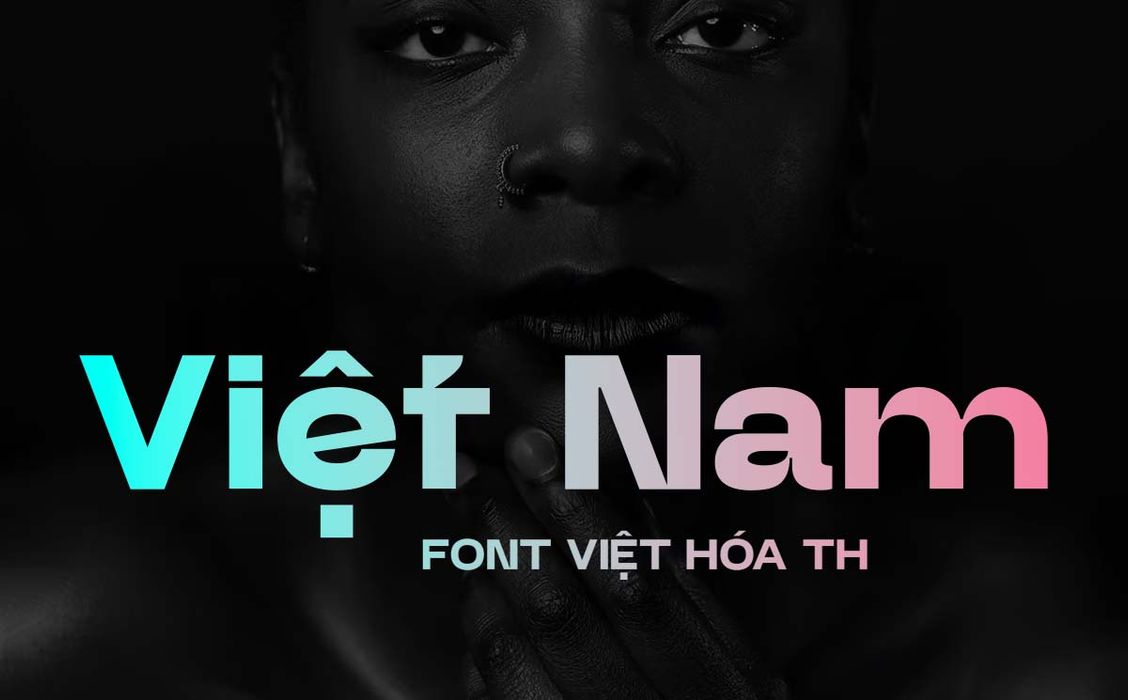
2. TH Guton - bộ font nhiều style cho dashboard và tài liệu sản phẩm
TH Guton phù hợp với các giao diện cần phân cấp rõ vì có nhiều style từ regular đến black. Đây là kiểu font đáng dùng cho dashboard, trang quản trị, app học tập, slide sản phẩm, tài liệu onboarding hoặc landing page có nhiều block nội dung.
Điểm mạnh của TH Guton là dễ tạo nhịp chữ: regular cho nội dung, medium cho label, bold cho số liệu và black cho heading ngắn. Khi dùng cho dashboard, bạn nên giữ khoảng cách dòng thoáng để số liệu và tiếng Việt có dấu không bị bí.
3. TH Algance - font tối giản cho landing page hiện đại
TH Algance có tinh thần sans-serif tối giản, phù hợp với landing page SaaS, website startup, thương hiệu công nghệ, portfolio agency hoặc trang giới thiệu sản phẩm số. Font tạo cảm giác hiện đại mà không cần quá nhiều hiệu ứng.
Với landing page, TH Algance nên dùng cho headline, subheading, đoạn mô tả ngắn và CTA. Nếu dùng cho dashboard nhiều dữ liệu, hãy kiểm tra trước các bảng số liệu nhỏ để đảm bảo chữ không quá mảnh.
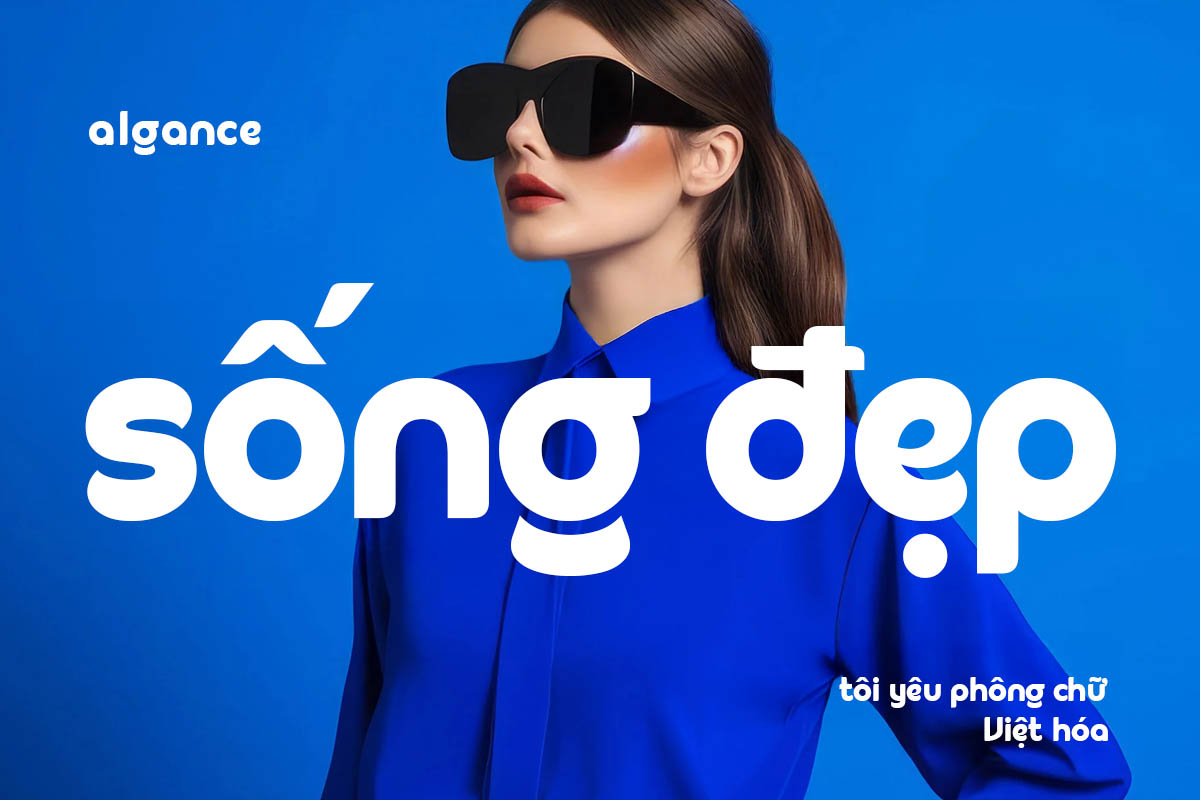
4. TH Giabe - sans-serif display cho hero và tiêu đề section
TH Giabe là font sans-serif display hiện đại, cá tính hơn các font UI trung tính. Font này hợp với hero landing page, banner trong app, tiêu đề section, cover sản phẩm, social post hoặc khu vực cần gây ấn tượng đầu tiên.
Không nên dùng TH Giabe cho toàn bộ body text nếu giao diện có nhiều chữ. Cách dùng tốt hơn là phối TH Giabe cho headline và dùng một font gọn hơn như TH Legacy Sans hoặc TH Guton cho nội dung phụ.
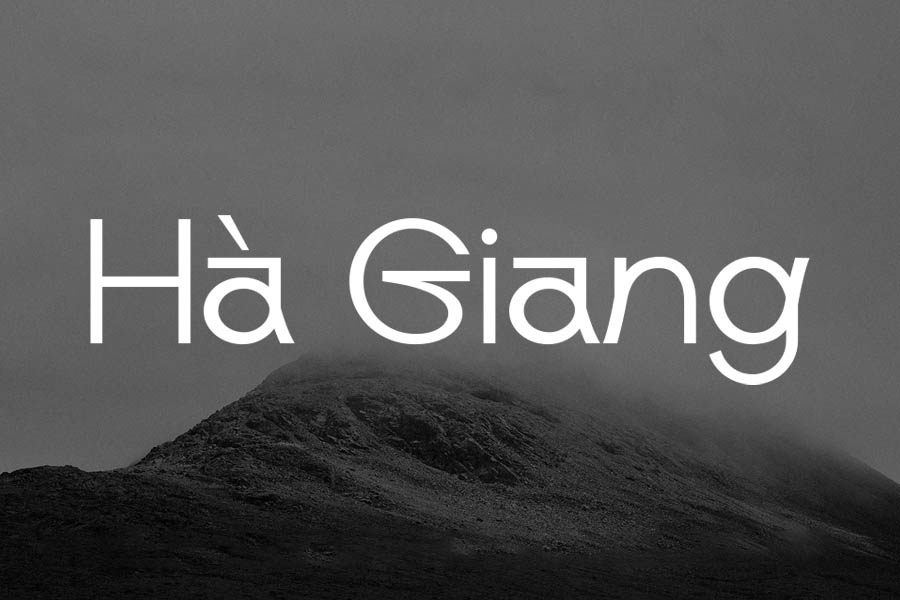
5. TH Grotley - luxury sans-serif cho landing page cao cấp
TH Grotley phù hợp với landing page sản phẩm cao cấp, app làm đẹp, dịch vụ tư vấn, khách sạn, clinic, spa hoặc thương hiệu cần cảm giác tinh tế nhưng vẫn hiện đại. Đây là font sans-serif có sắc thái luxury, dễ dùng hơn các font serif mảnh khi thiết kế giao diện.
Bạn có thể dùng TH Grotley cho heading, tên gói dịch vụ, số liệu nổi bật và CTA. Với đoạn mô tả dài, nên tăng line-height và giữ màu chữ đủ tương phản để giao diện không bị nhẹ quá.
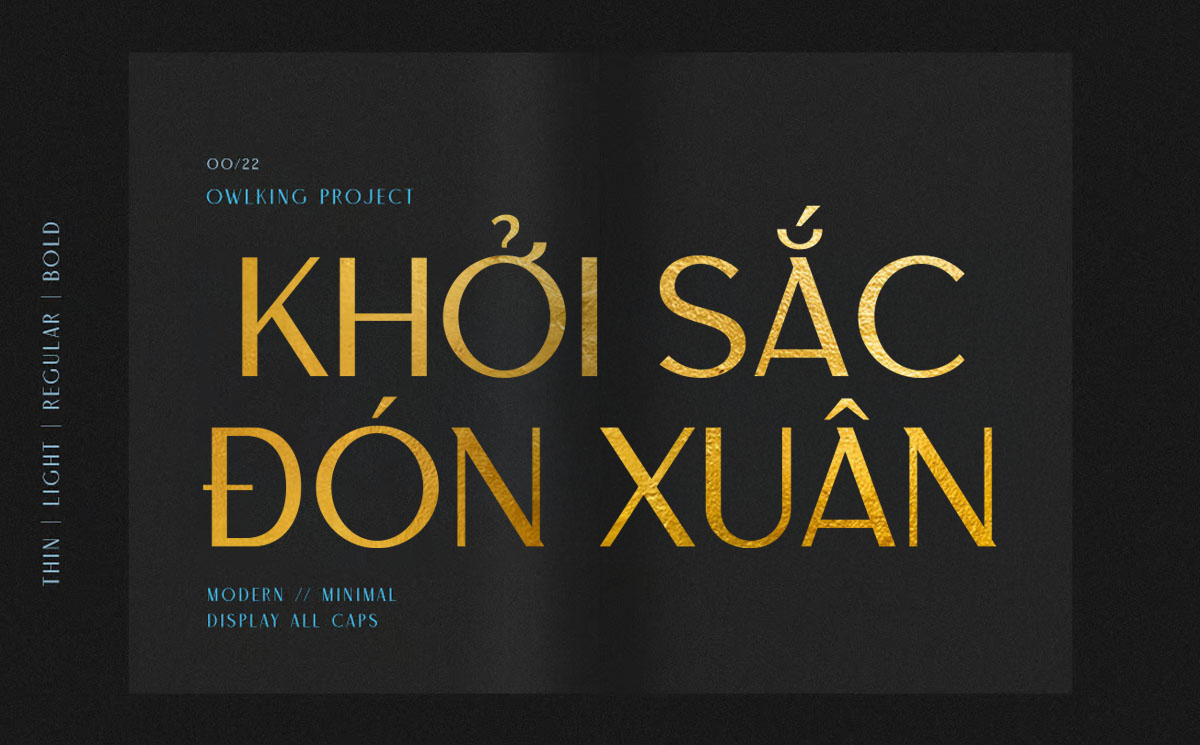
6. TH Selaris - font hiện đại cho app làm đẹp và landing page dịch vụ
TH Selaris hợp với các giao diện trong lĩnh vực làm đẹp, skincare, spa, clinic, tư vấn cá nhân hoặc dịch vụ lifestyle. Font tạo cảm giác hiện đại, mềm và có sự chăm chút, phù hợp với landing page cần độ tin cậy lẫn tính thẩm mỹ.
Khi dùng TH Selaris, hãy đặt font ở những khu vực cần cảm giác thương hiệu: headline, tên dịch vụ, card lợi ích, testimonial hoặc CTA. Với dashboard nội bộ nhiều bảng dữ liệu, nên phối thêm font phụ rõ hơn.
Xem mẫu và tải font TH Selaris Việt hóa.
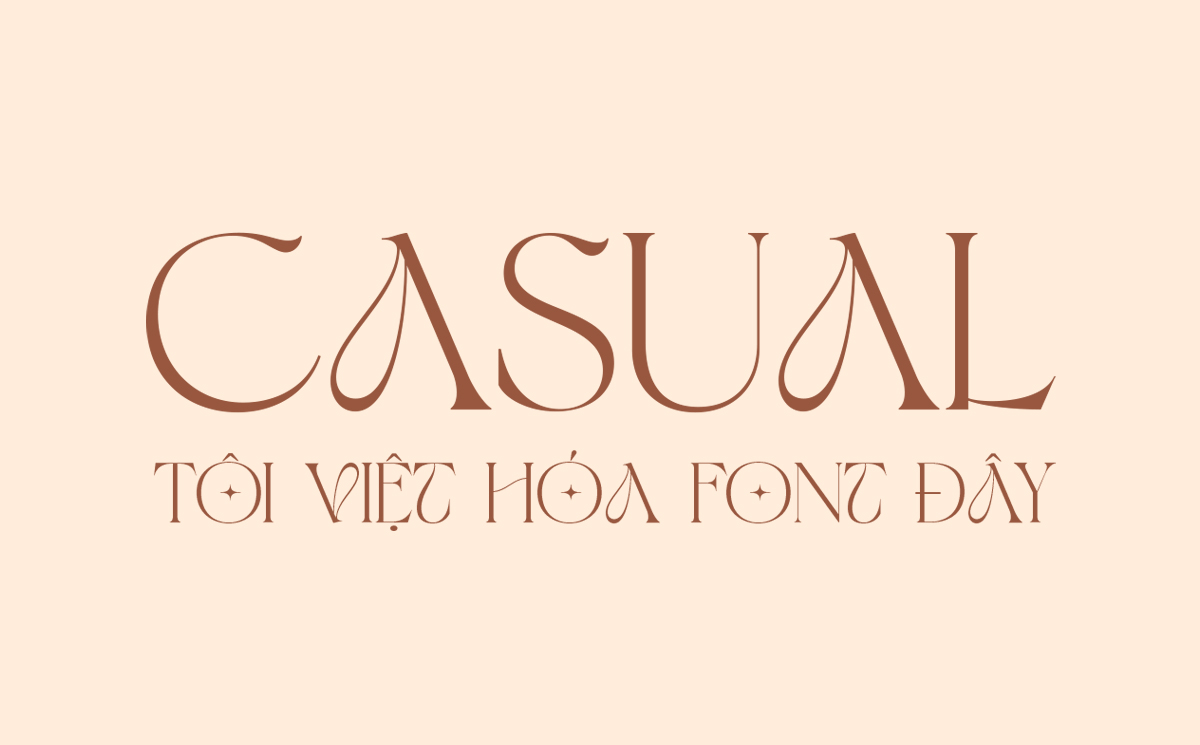
7. TH Milkalte - font hiện đại cho landing page cân sức, wellness và dịch vụ
TH Milkalte phù hợp với landing page wellness, fitness nhẹ, dịch vụ chăm sóc sức khỏe, app lifestyle hoặc trang giới thiệu sản phẩm có phong cách sạch và sang. Font có vẻ hiện đại, hợp với các layout nền sáng, ảnh sản phẩm và nhiều khoảng trắng.
Bạn nên dùng TH Milkalte cho tiêu đề, nhãn tính năng và các cụm chữ ngắn. Nếu landing page có nhiều đoạn mô tả dài, hãy kiểm tra độ đọc trên mobile vì người dùng thường đọc ở cỡ chữ nhỏ hơn desktop.
Xem mẫu và tải font TH Milkalte Việt hóa.
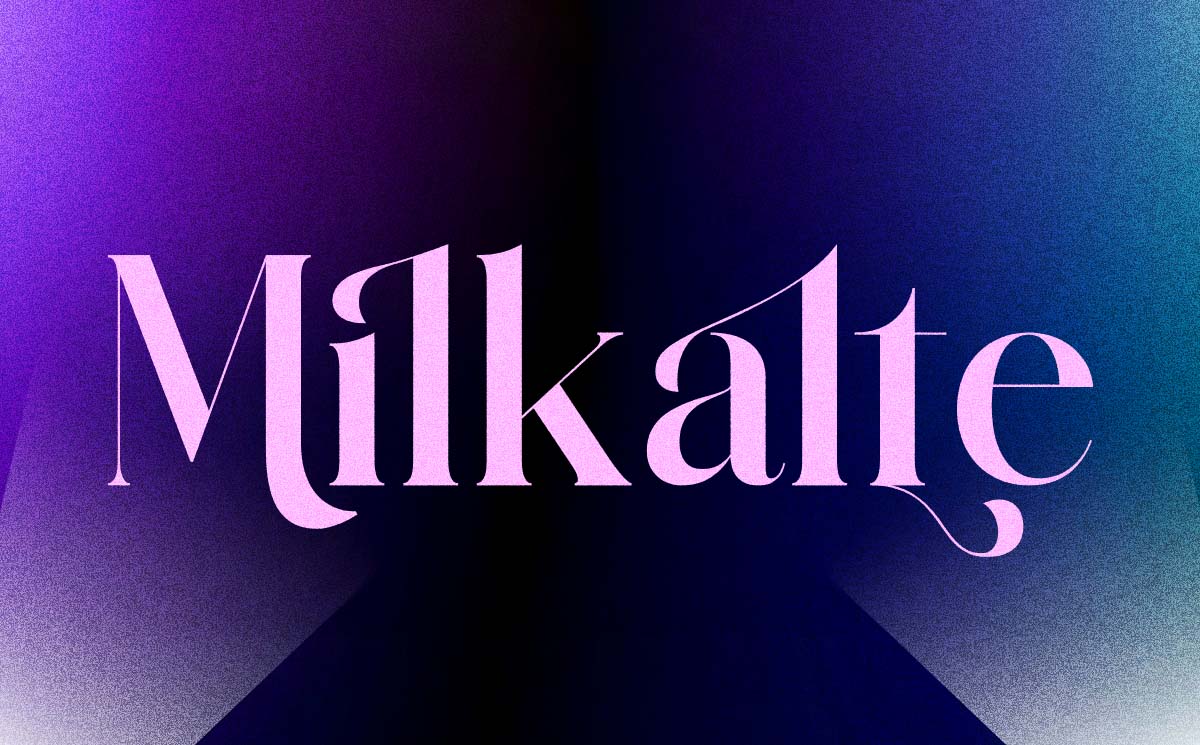
8. TH Mattire - font sang trọng cho website thương hiệu và trang giới thiệu
TH Mattire hợp với website thương hiệu, landing page dịch vụ cao cấp, trang giới thiệu agency, thời trang, mỹ phẩm hoặc các sản phẩm cần cảm giác tinh gọn. Font có chất hiện đại và sang, nhưng không quá kịch tính như font display poster.
Trong UI, TH Mattire nên dùng cho heading, số liệu nổi bật, tên gói dịch vụ hoặc section title. Với phần mô tả, bảng giá và form, hãy giữ chữ đủ lớn và khoảng dòng thoáng để tăng khả năng đọc.
Xem mẫu và tải font TH Mattire Việt hóa.
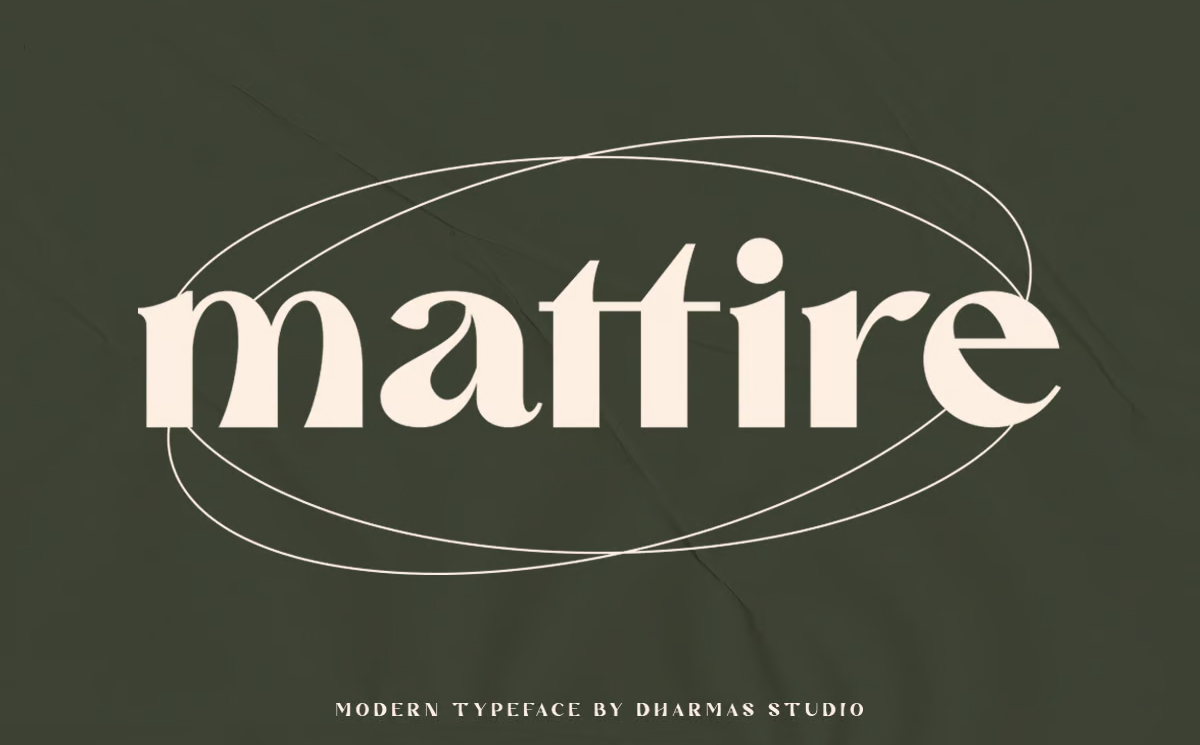
9. TH Bevas - font luxury hiện đại cho landing page sản phẩm
TH Bevas phù hợp với landing page mỹ phẩm, thời trang, phụ kiện, trang sức, khóa học premium hoặc dịch vụ tư vấn. Font có cảm giác luxury hiện đại, giúp phần hero và headline nhìn có giá trị hơn.
Với app hoặc dashboard, TH Bevas nên dùng tiết chế cho banner, empty state, onboarding hoặc tiêu đề lớn. Không nên dùng font này cho toàn bộ bảng dữ liệu vì sắc thái thương hiệu có thể lấn át tính thực dụng của UI.
Xem mẫu và tải font TH Bevas Việt hóa.
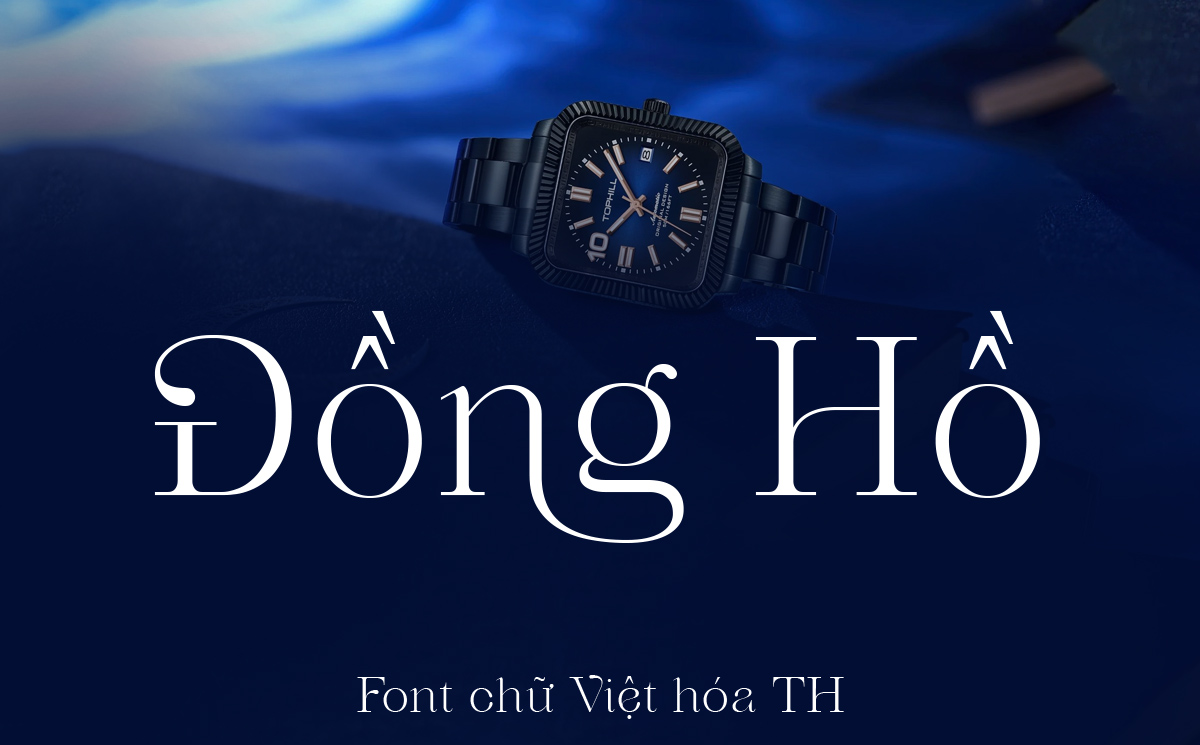
10. TH Retalin Regular - font mềm cho landing page spa và dịch vụ cá nhân
TH Retalin Regular hợp với landing page spa, làm đẹp, yoga, tư vấn sức khỏe, dịch vụ chăm sóc cá nhân hoặc thương hiệu cần cảm giác nhẹ. Font này giúp giao diện mềm hơn mà vẫn giữ được sự gọn gàng.
Bạn có thể dùng TH Retalin Regular cho headline, tên dịch vụ, section giới thiệu và CTA nhẹ nhàng. Với phần FAQ, điều khoản, bảng giá hoặc form đặt lịch, nên phối thêm font sans-serif rõ hơn để người dùng đọc nhanh.
Xem mẫu và tải font TH Retalin Regular Việt hóa.
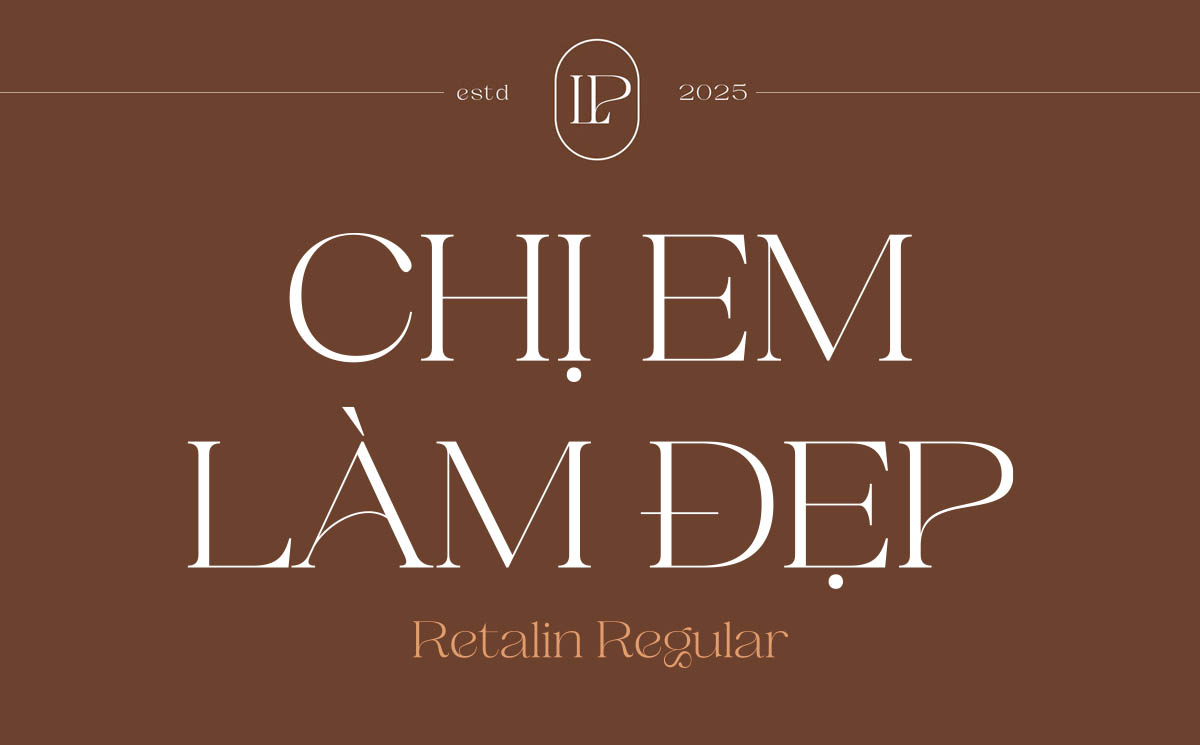
11. TH Galvitra - font display hiện đại cho hero landing page
TH Galvitra là font display hiện đại, phù hợp với hero section, banner quảng cáo, trang giới thiệu sản phẩm, landing page chiến dịch hoặc thumbnail cho sản phẩm số. Font giúp phần đầu trang có lực hơn, đặc biệt khi headline ngắn.
Với giao diện app, TH Galvitra nên dùng như font accent, không dùng cho menu và nội dung nhỏ. Cách phối an toàn là TH Galvitra cho headline, TH Legacy Sans hoặc TH Guton cho body và label.
Xem mẫu và tải font TH Galvitra Việt hóa.
12. TH Gyokz - font công nghệ cho app, SaaS và dashboard
TH Gyokz có chất công nghệ rõ, phù hợp với landing page SaaS, app AI, dashboard kỹ thuật, sản phẩm bảo mật, fintech, gaming tool hoặc website startup. Font giúp giao diện có cảm giác hiện đại và sắc hơn.
Khi dùng TH Gyokz, hãy chú ý vai trò của font. Font rất hợp cho headline, metric card, banner, logo text hoặc tiêu đề tính năng. Với nội dung dài, bạn nên dùng font phụ trung tính để tránh giao diện bị căng.
Xem mẫu và tải font TH Gyokz Việt hóa.
13. TH Colombo Sans - font hoài cổ nhưng dễ đọc cho website thương hiệu Việt
TH Colombo Sans không phải kiểu UI công nghệ thuần túy, nhưng rất đáng dùng cho website thương hiệu Việt, quán cafe, đặc sản, du lịch địa phương, bảo tàng nhỏ, studio thủ công hoặc landing page có cảm giác hoài niệm. Font giữ được cấu trúc sans-serif nên dễ đọc hơn nhiều font retro trang trí.
Bạn có thể dùng TH Colombo Sans cho headline, menu, card sản phẩm và các đoạn giới thiệu ngắn. Nếu làm dashboard hiện đại, font này chỉ nên dùng trong phần brand hoặc landing page bên ngoài, không nên dùng cho bảng số liệu dày đặc.
Xem mẫu và tải font TH Colombo Sans Việt hóa.
14. TH Qara - font thời trang hiện đại cho landing page visual mạnh
TH Qara phù hợp với landing page thời trang, lookbook, local brand, mỹ phẩm, phụ kiện hoặc campaign social dẫn về website. Font có chất thời trang hiện đại, dùng tốt cho headline, tên bộ sưu tập và section title.
Với UI nhiều thao tác như app quản lý đơn hàng hoặc dashboard, TH Qara nên dùng hạn chế. Nhưng với landing page visual mạnh, font này giúp thương hiệu có cá tính hơn so với các sans-serif quá trung tính.
Xem mẫu và tải font TH Qara Việt hóa.
15. TH Valoer - font thẩm mỹ cho landing page spa, beauty và lifestyle
TH Valoer hợp với landing page spa, beauty, thẩm mỹ, lifestyle, studio cá nhân hoặc dịch vụ tư vấn cao cấp. Font giúp giao diện có cảm giác chăm chút và tinh tế, đặc biệt khi đi cùng ảnh sản phẩm đẹp và bảng màu nhẹ.
Bạn nên dùng TH Valoer cho headline, tên dịch vụ, banner ưu đãi và các cụm chữ ngắn. Với form đặt lịch, bảng giá hoặc nội dung cần quét nhanh, hãy phối font phụ rõ ràng để giữ trải nghiệm người dùng.
Xem mẫu và tải font TH Valoer Việt hóa.
Gợi ý phối font cho từng loại giao diện
App quản lý, dashboard và SaaS
Với app nhiều dữ liệu, hãy ưu tiên TH Legacy Sans hoặc TH Guton làm font chính. Hai font này dễ tạo hệ thống chữ cho menu, label, body text, bảng dữ liệu và nút bấm. Nếu cần điểm nhấn công nghệ, có thể thêm TH Gyokz cho headline hoặc metric card.
Landing page startup và sản phẩm số
Landing page cần vừa rõ vừa có cá tính. Bạn có thể dùng TH Algance hoặc TH Legacy Sans cho hệ thống chữ chính, sau đó thêm TH Giabe, TH Galvitra hoặc TH Gyokz cho hero headline. Cách phối này giúp trang có lực mà vẫn đọc tốt trên mobile.
Website beauty, spa và dịch vụ cao cấp
Với spa, skincare, clinic hoặc dịch vụ lifestyle, hãy thử TH Grotley, TH Selaris, TH Retalin Regular, TH Bevas hoặc TH Valoer. Nhóm này tạo cảm giác tinh tế hơn font UI trung tính. Tuy nhiên, các phần như form, FAQ, bảng giá và điều khoản vẫn nên dùng cỡ chữ đủ lớn.
Website thương hiệu Việt, cafe và sản phẩm địa phương
Nếu website cần cảm giác hoài cổ hoặc thủ công, TH Colombo Sans là lựa chọn đáng thử. Font này có bản sắc nhưng vẫn đủ gọn để dùng trong giao diện. Bạn có thể phối với ảnh sản phẩm, texture giấy, màu nâu, kem, đỏ trầm hoặc xanh rêu.
Checklist trước khi dùng font cho UI tiếng Việt
- Gõ thử các cụm tiếng Việt có nhiều dấu như "quản lý tài khoản", "đăng ký dùng thử", "thanh toán thành công".
- Kiểm tra font ở cỡ 12px, 14px, 16px và 24px.
- Test trên mobile, đặc biệt với nút bấm và form.
- Không dùng font display cho toàn bộ body text.
- Với dashboard, ưu tiên font có nhiều weight hoặc dễ tạo phân cấp.
- Kiểm tra line-height để dấu tiếng Việt không bị chạm dòng trên dưới.
- Luôn xem giao diện ở trạng thái thật: bảng dữ liệu, empty state, modal, alert, tooltip và CTA.
Font giao diện app Việt hóa cần rõ, ổn định và phù hợp với tính cách sản phẩm. Nếu cần một font chính an toàn cho dashboard hoặc SaaS, hãy bắt đầu với TH Legacy Sans và TH Guton. Nếu làm landing page hiện đại, TH Algance, TH Giabe, TH Galvitra hoặc TH Gyokz sẽ giúp phần hero nổi bật hơn. Với sản phẩm beauty, spa và lifestyle, TH Grotley, TH Selaris, TH Retalin Regular, TH Bevas và TH Valoer là những lựa chọn đáng thử.